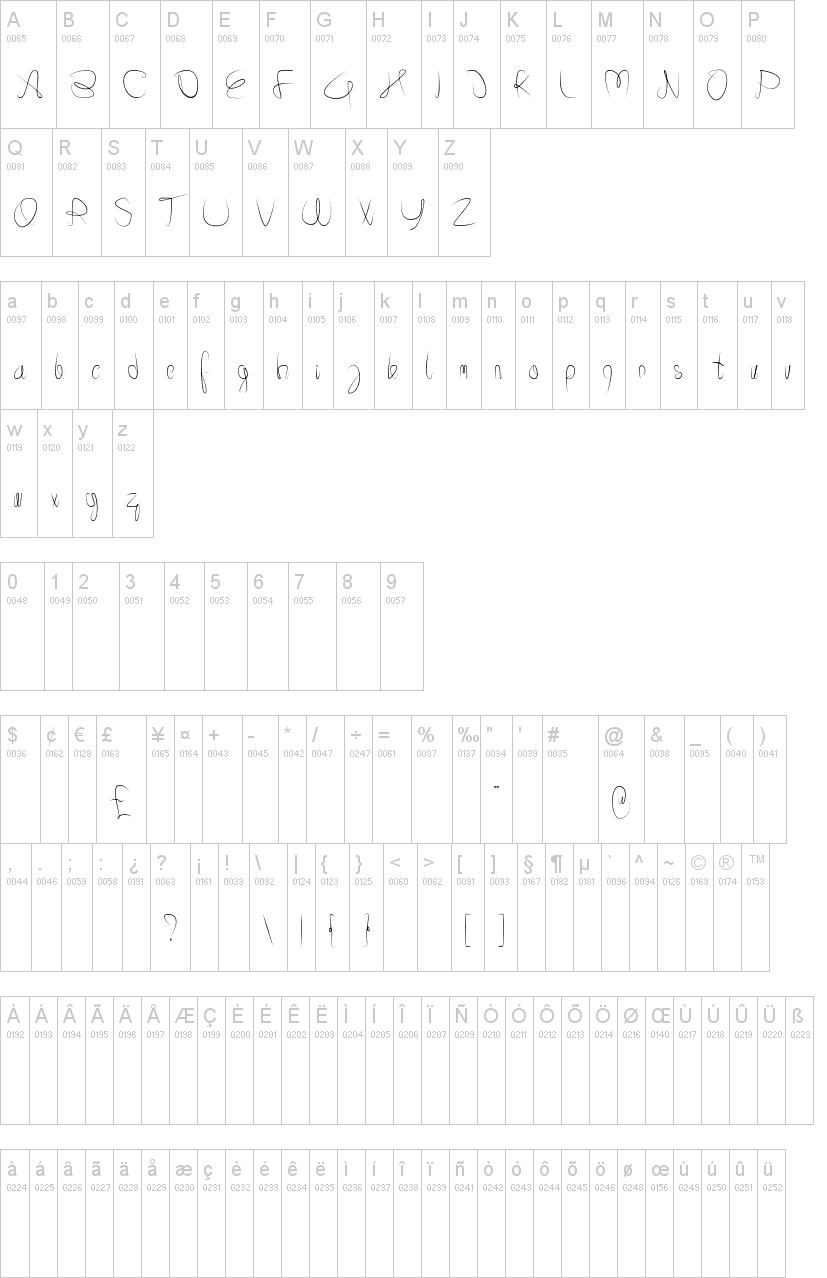
Minnesotta
Minnesota字体是一种源自20世纪30年代的美式手写体,它的特点是粗细相间的笔画,具有柔和的曲线,给人一种温暖的感觉。Minnesota字体的字体结构非常简洁,不同的字母之间的间距也很紧凑。它的字形更加精致,有一种温柔的感觉,给人一种温暖的感觉,可以用在婚礼邀请函、海报等设计中。Minnesota字体还可以用于网页设计、平面设计、宣传单等等,可以使文字更加精致,给读者以温暖的感觉。
Minnesotta是一款非常不错的手写艺术字体,具有很好的视觉感,适合于文化类的宣传设计、商业类品牌的广告和产品包装设计以及个性化文字排版等较多场景。